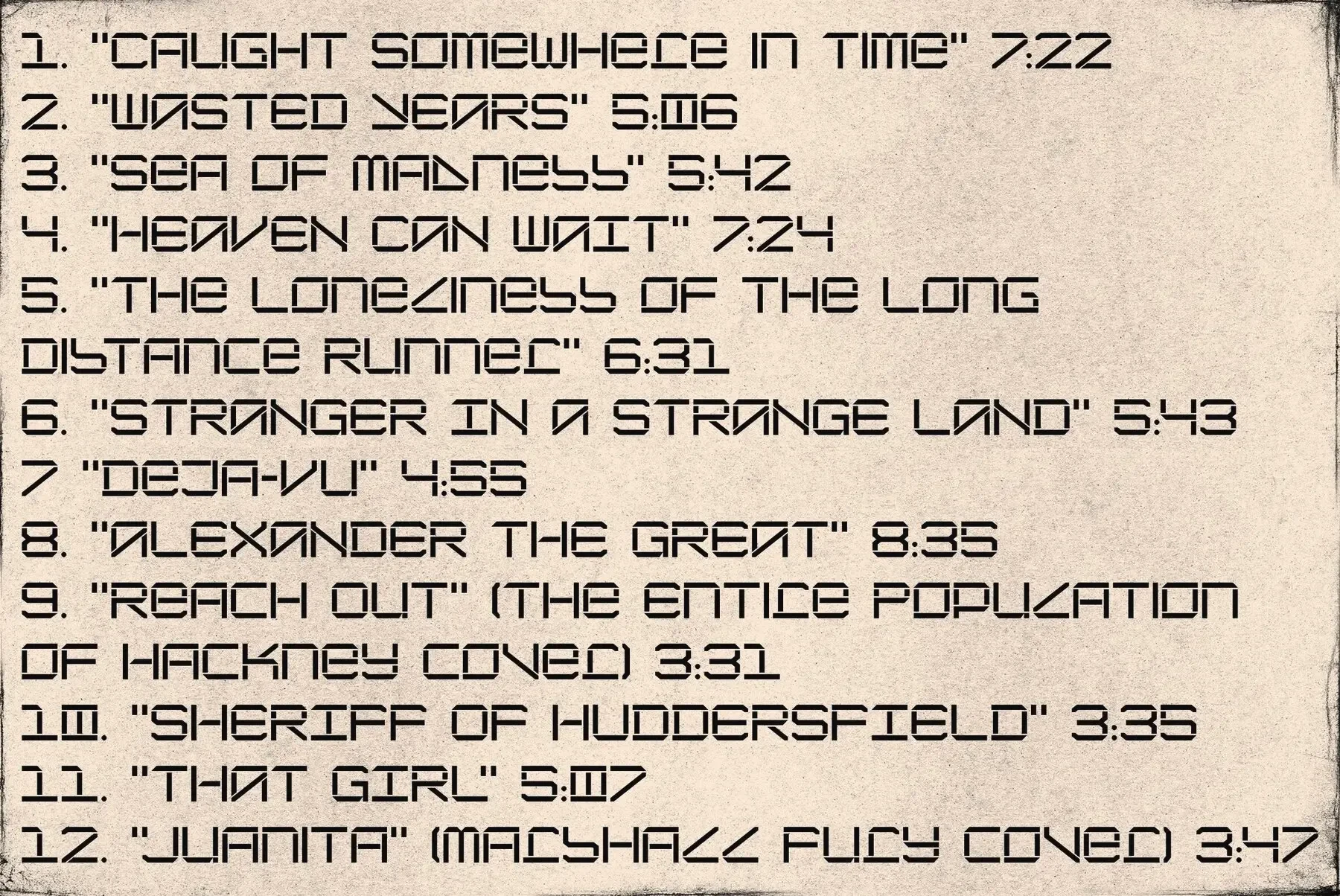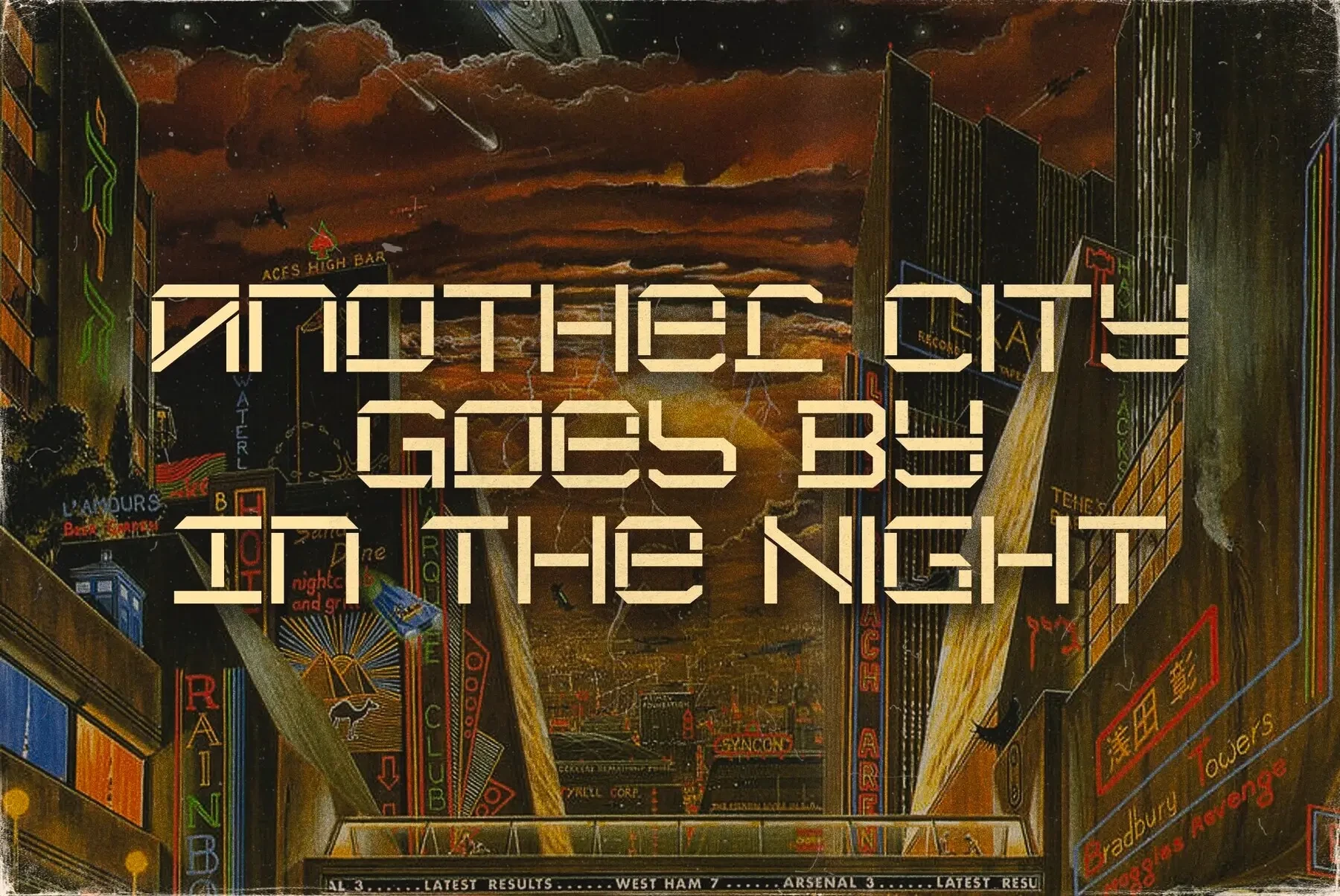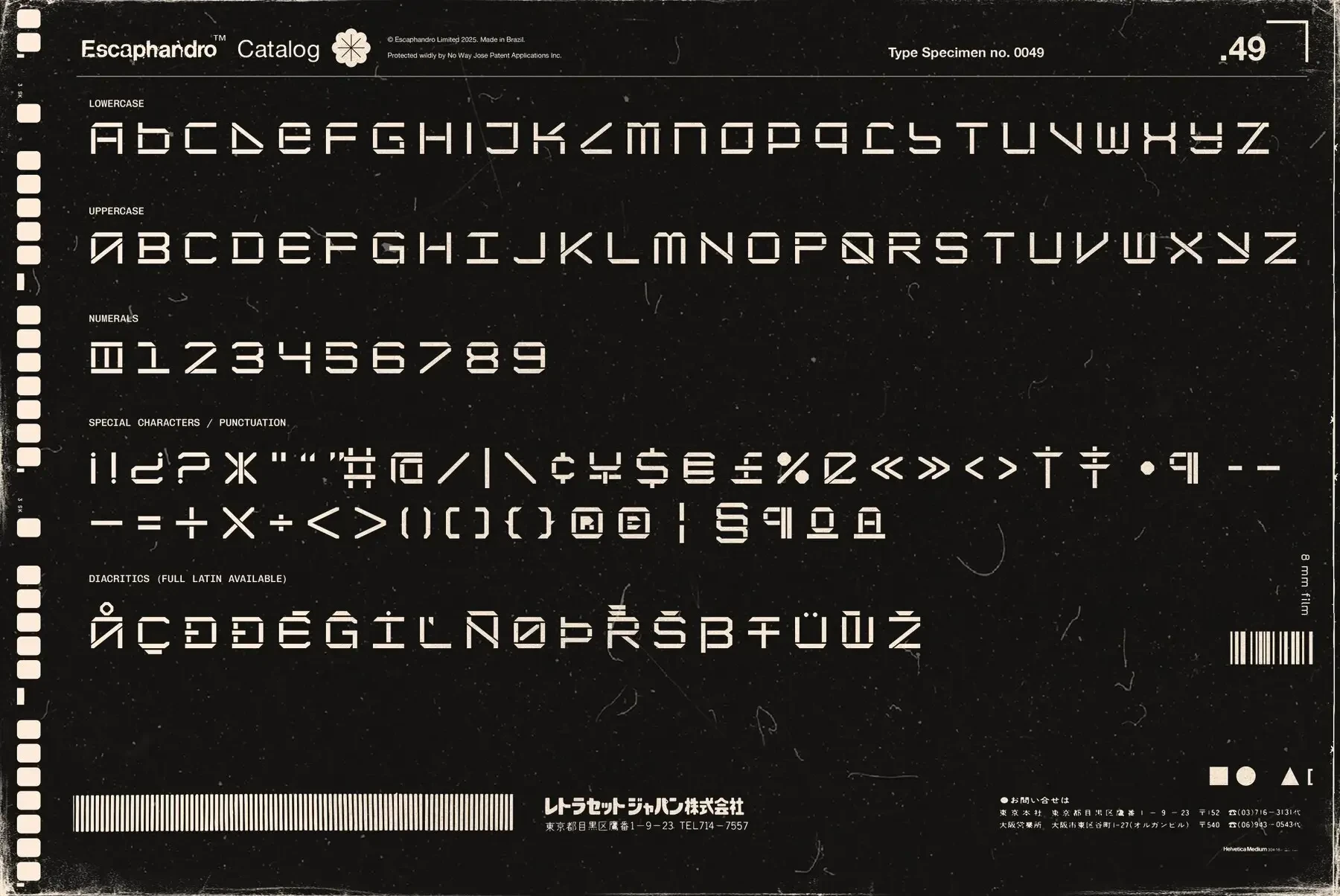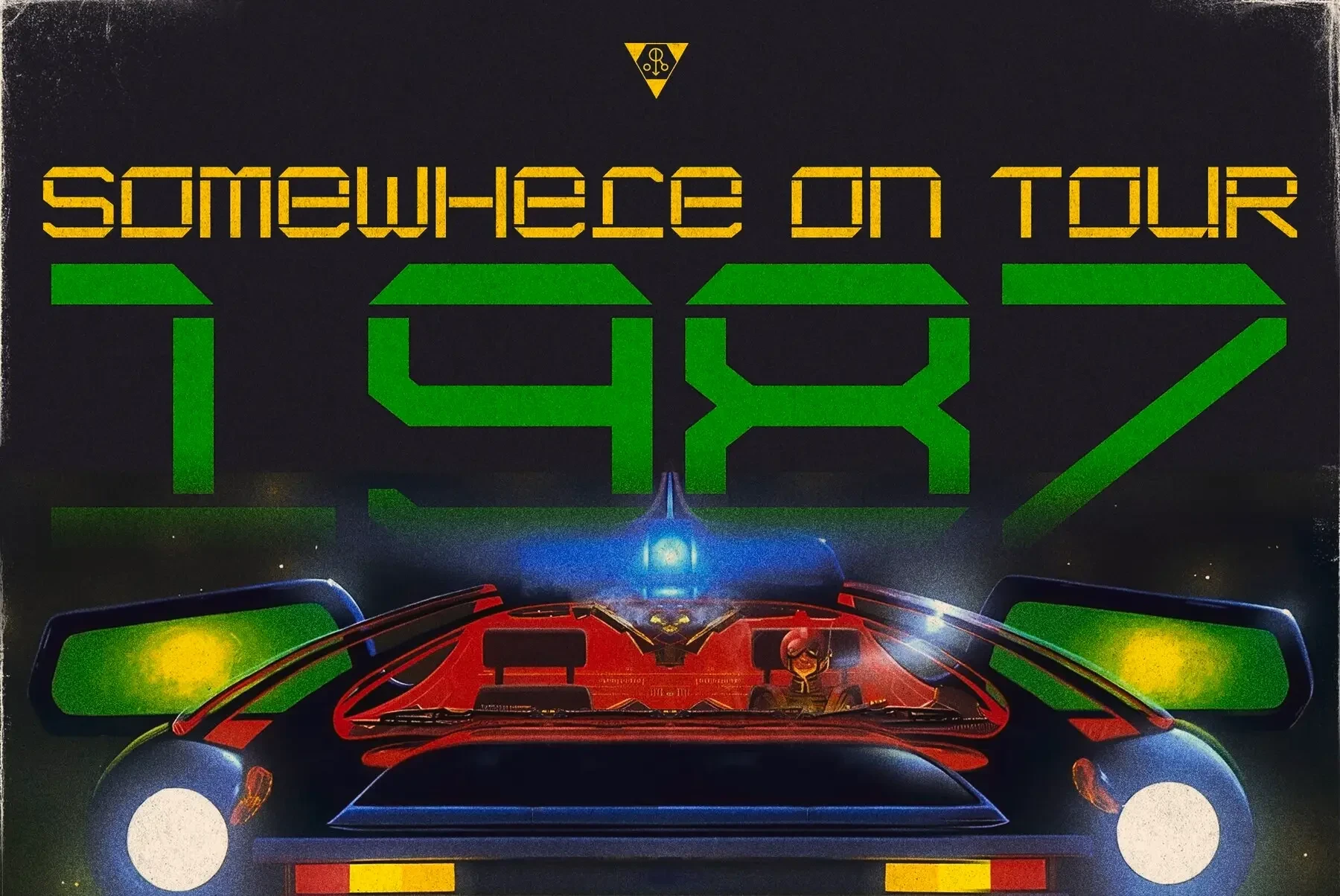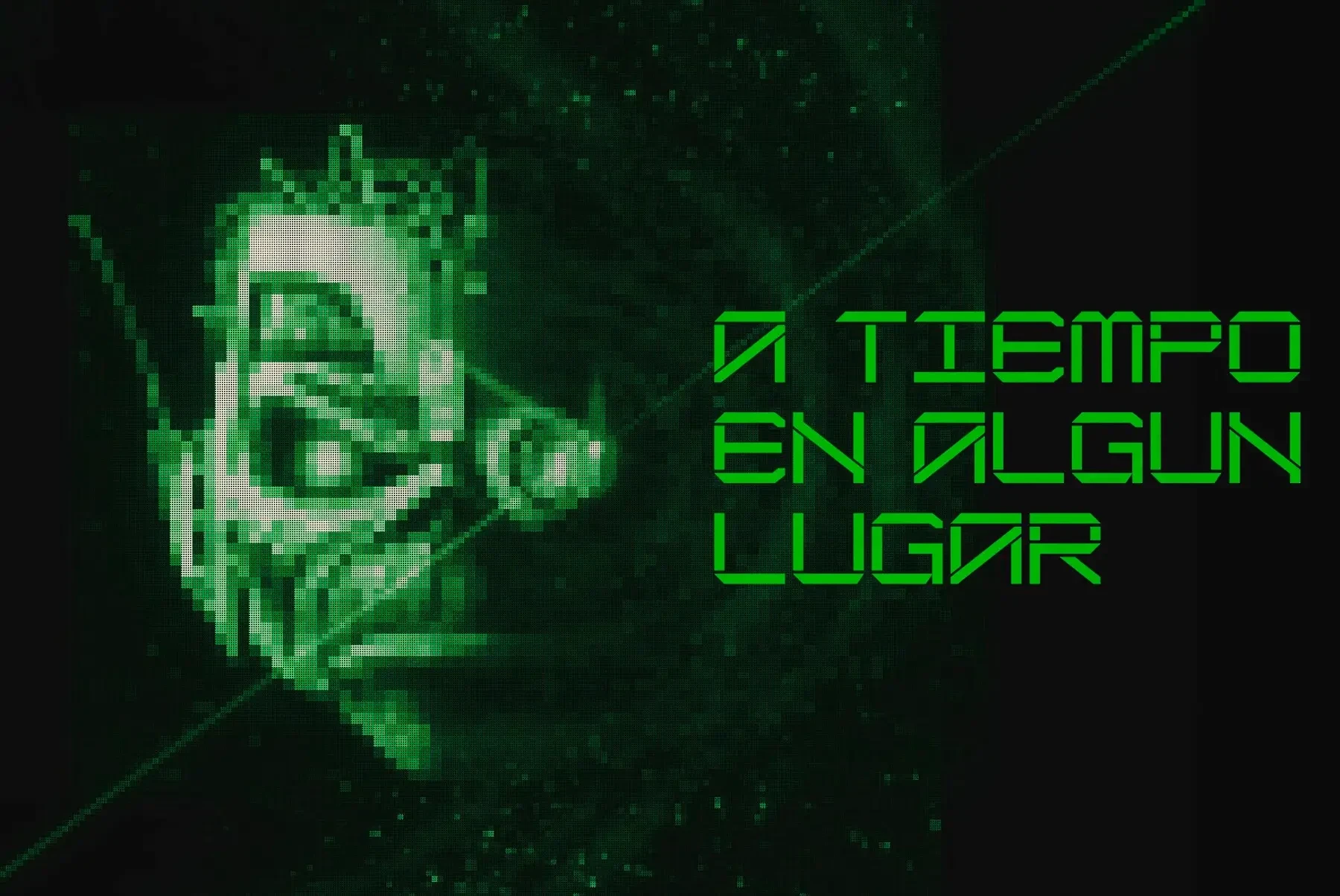
Wasted Years thể hiện tinh hoa của phong cách tương lai hoài cổ với thiết kế stencil kim loại đặc trưng. Được lấy cảm hứng từ bìa đĩa nhạc Argentina khó tìm của bản hit Iron Maiden năm 1986, font chữ này hồi sinh một phong cách thẩm mỹ gần như bị lãng quên. Được tạo ra bằng cách tỉ mỉ tái tạo từng ký tự từ những tài liệu tham khảo hạn chế, Wasted Years trở thành một font chữ số hoàn chỉnh.
- Thiết kế stencil độc đáo lấy cảm hứng từ bìa đĩa nhạc cổ điển.
- Kết xuất số hoàn chỉnh từ những tài liệu tham khảo ký tự hiếm hoi.
- Kết hợp thẩm mỹ tương lai hoài cổ với cảm giác kim loại táo bạo.